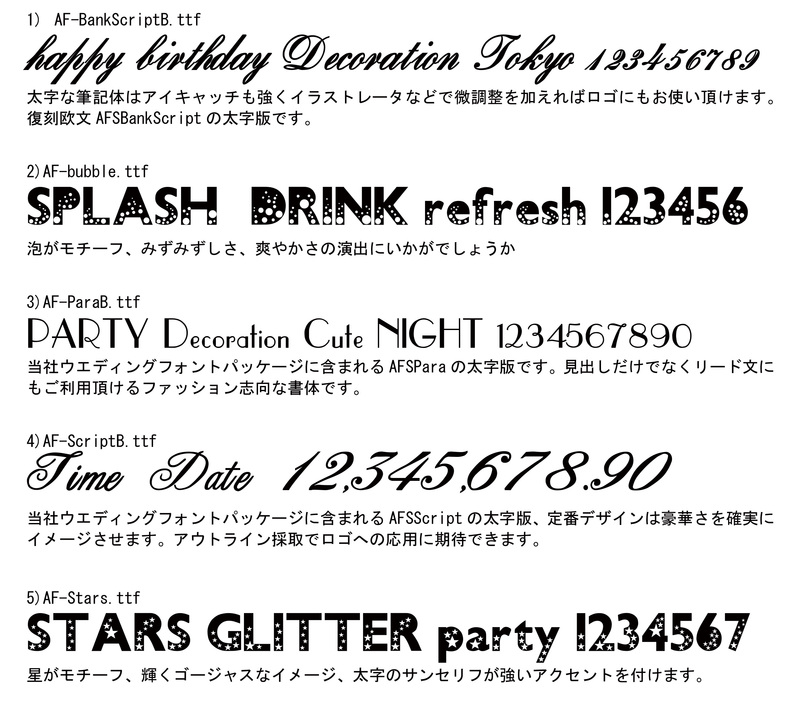
【収録書体】
・AF-BankScriptB
・AF-bubble
・AF-ParaB
・AF-ScriptB
・AF-Stars
※プレビューフォントは「AF-bubble」です。
太めの欧文デザインフォント、5書体セットです。
見出し小見出しなどアイキャッチ用に可愛らしさと愉しさを求める場所にご利用ください。